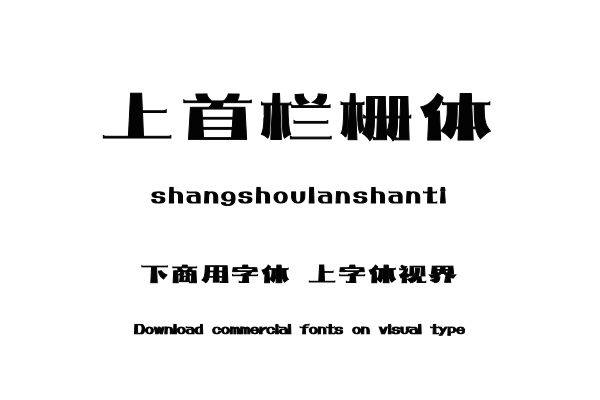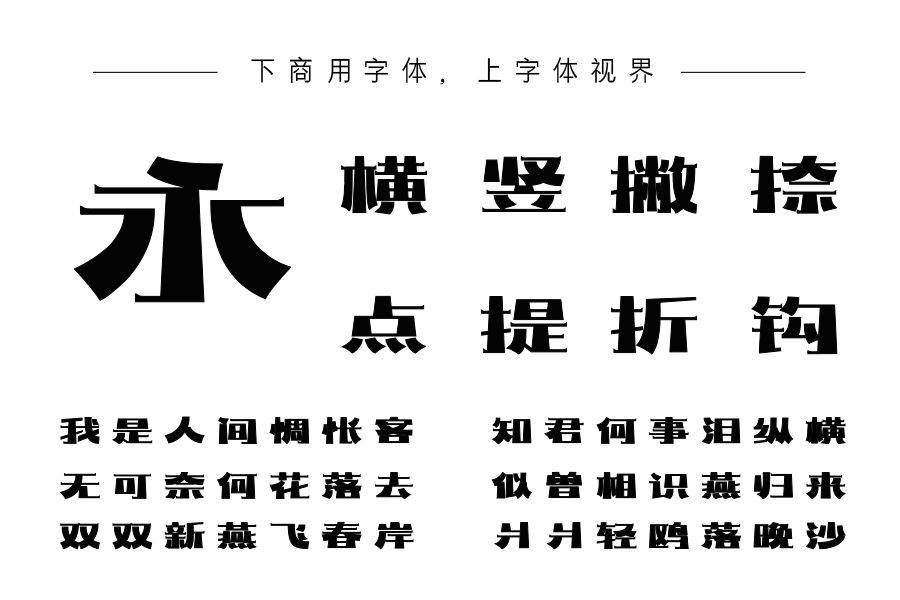
上首栏栅体字体整体稳重。竖笔上细下粗,与纤细的横笔形成鲜明对比,使整个画面保持协调美。购买须知:“下载服务费”与“字体VIP”所获得字体 仅用于个人非商用, 商用请联系付费授权。本字体为电脑用字,手机没有root权限不支持直接手机换字(手机如何root,请自行百度搜索教程)。购买前请先 了解清楚后再付款 ,字体为虚拟产品无法回收 一旦购买不支持退款。